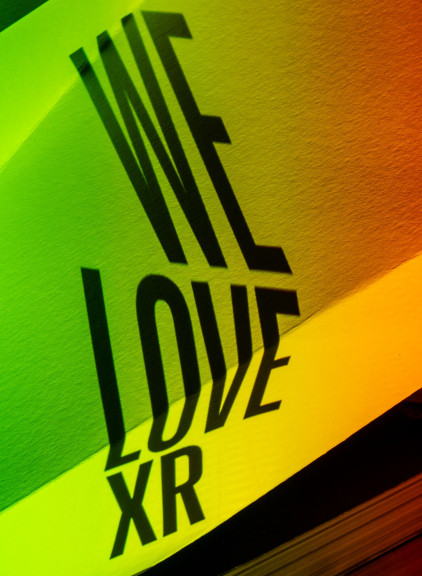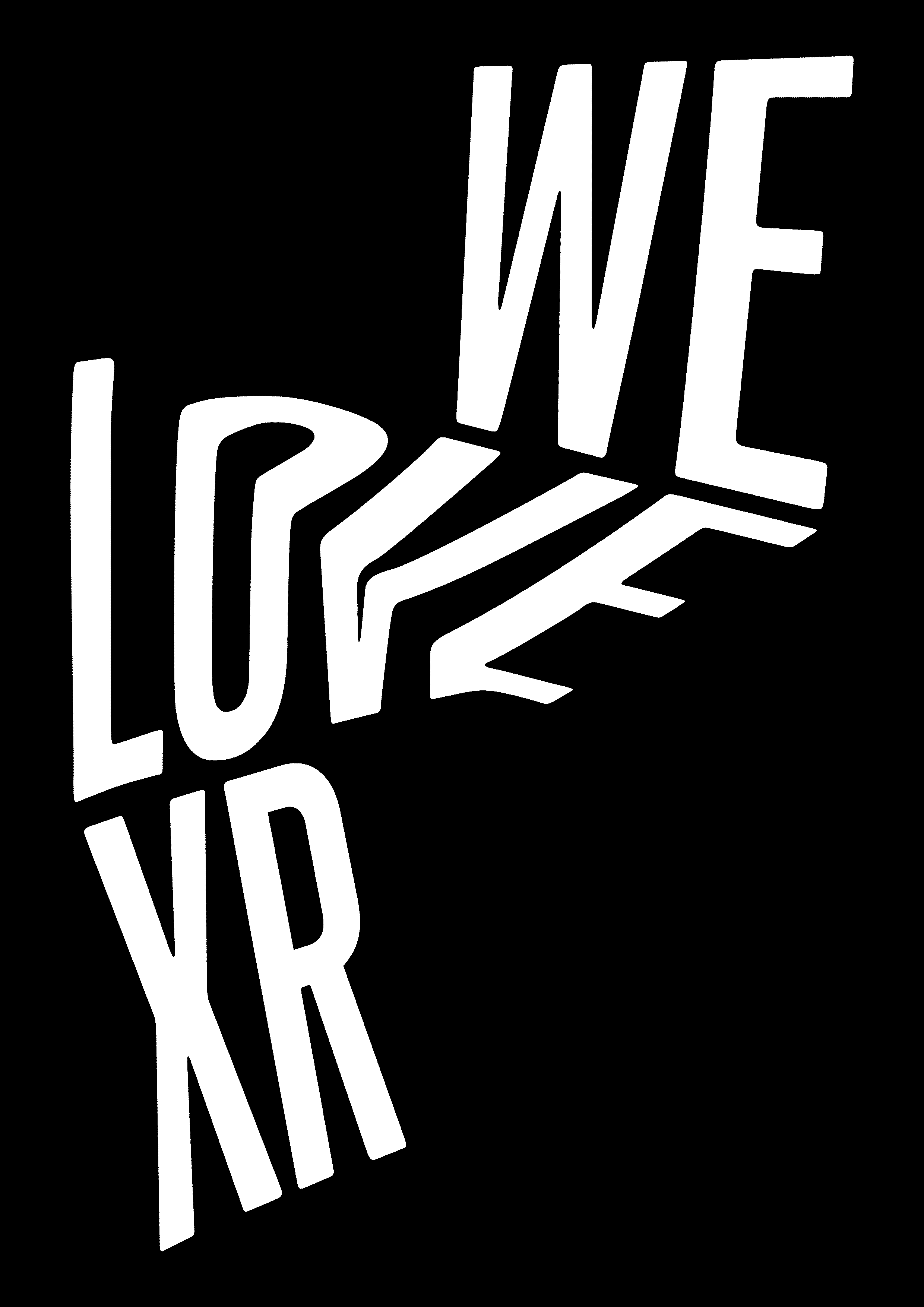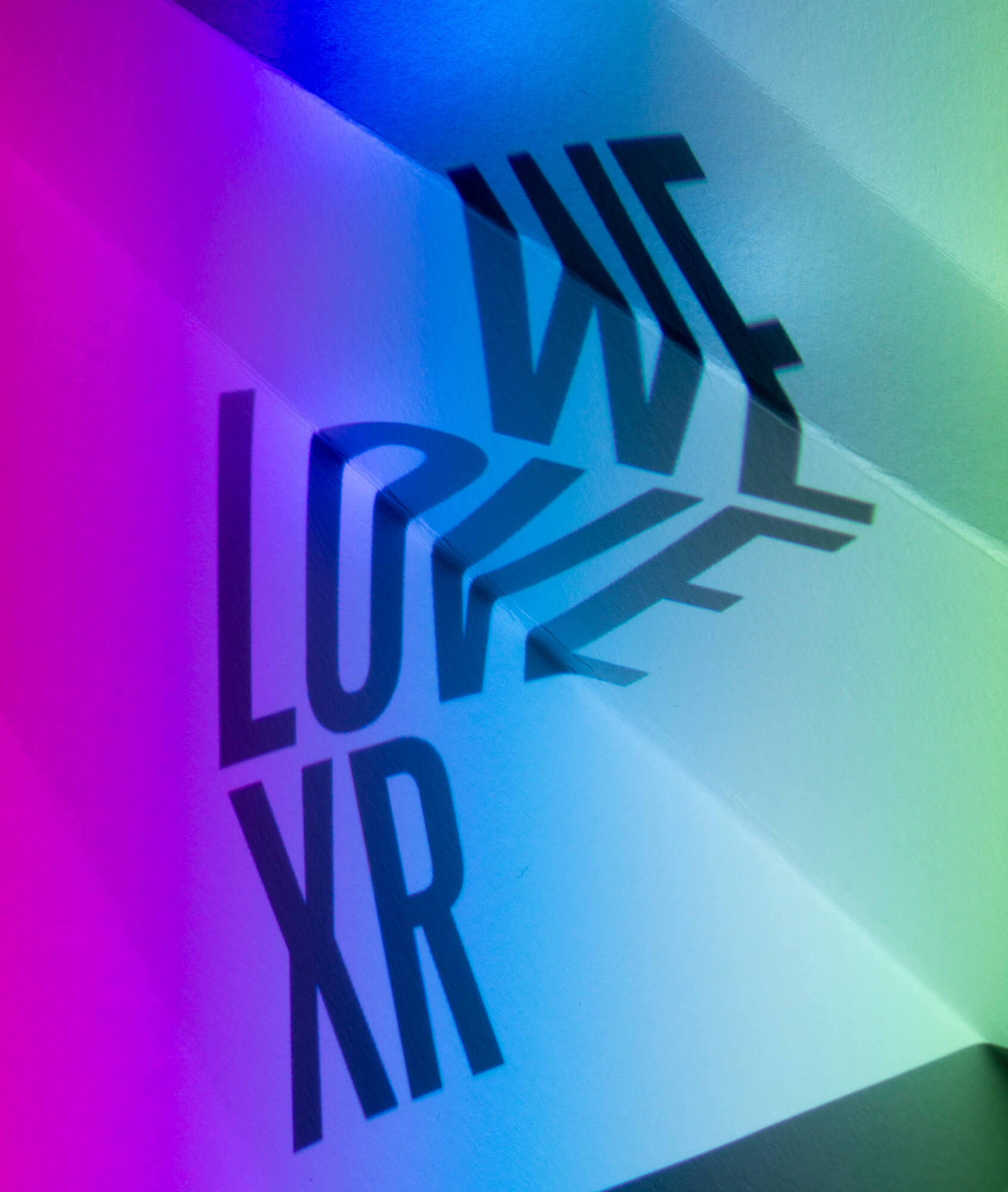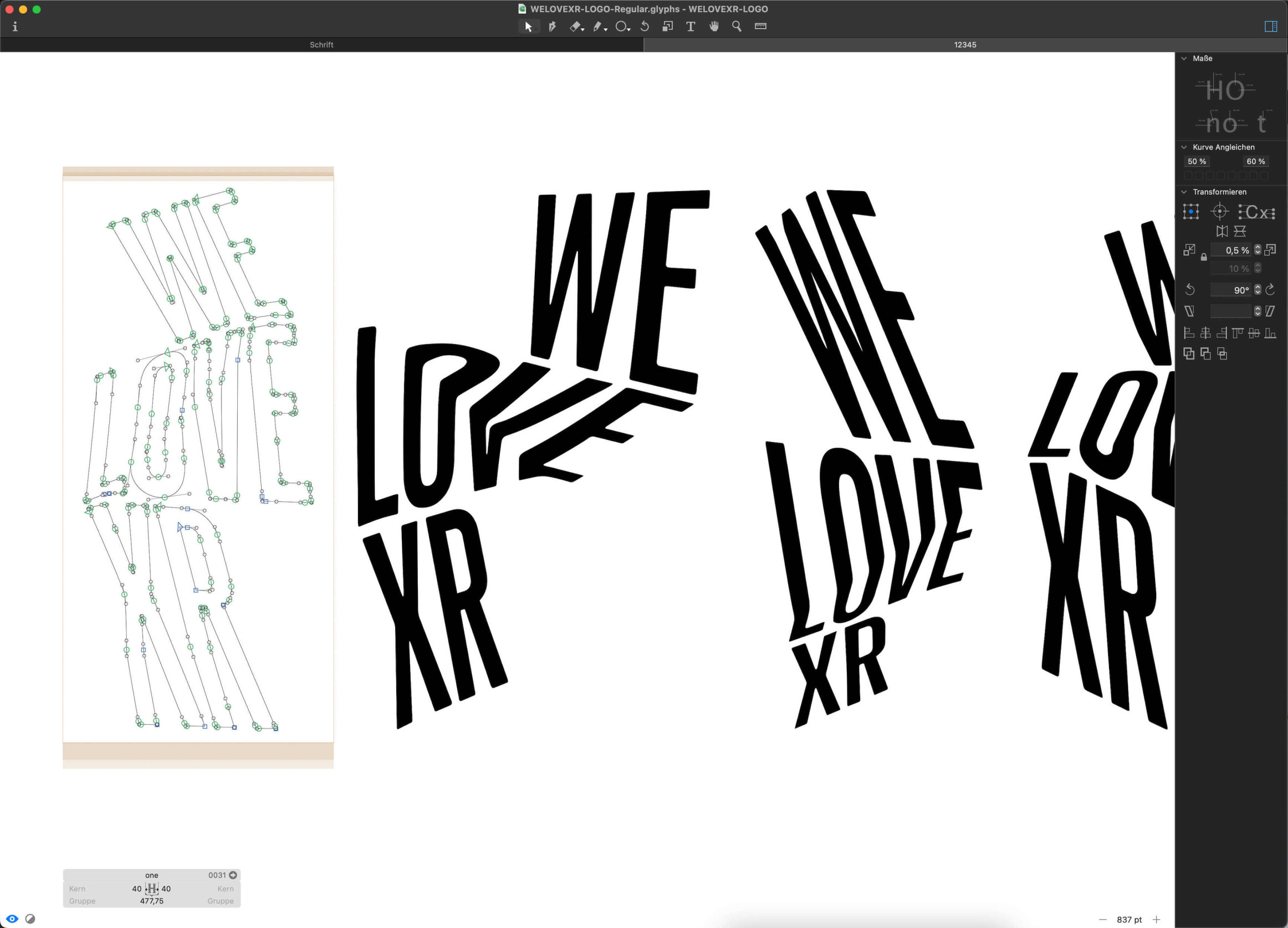
WELOVEXR
Logogestaltung für WE LOVE XR — ein internationales Gemeinschaftsprojekt einer Vielzahl an Künstler*innen aus unterschiedlichen Bereichen, die die Möglichkeiten der Extended Reality erforschen. Initiiert und kuratiert von OBJ.Studio wird das Projekt von der AMBION GmbH im SUPEROOM XR Studio ermöglicht.
Wir haben einen simplen 3D Effekt aus einer einfachen schwarz-weiß Logotype kreiert, um so den Prozess darzustellen, der im SUPEROOM XR durch eine LED Wand ermöglicht wird.
Schrift: Trade Gothic Next Soft Rounded von Linotype (Akira Kobayashi)
Schrift: Norbert von Philipp Neumeyer